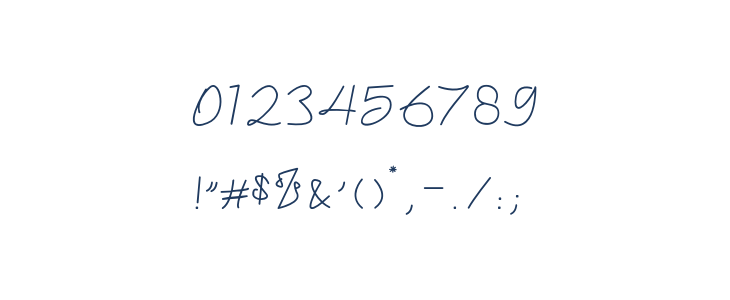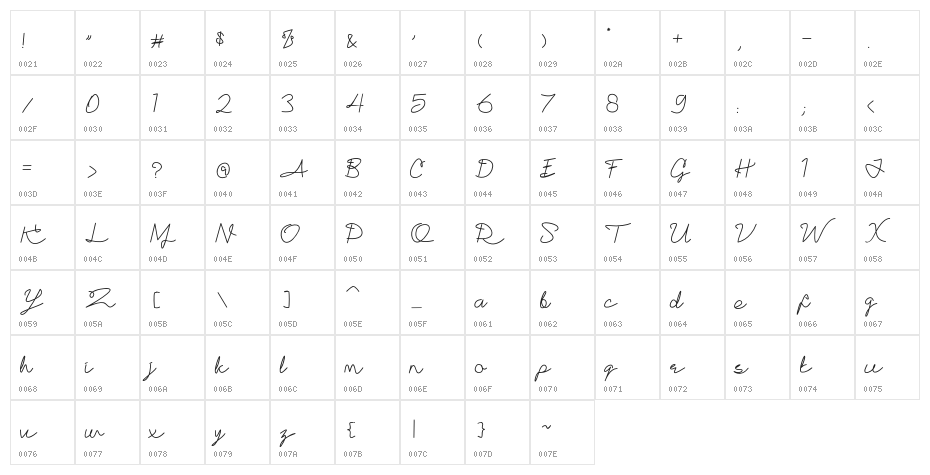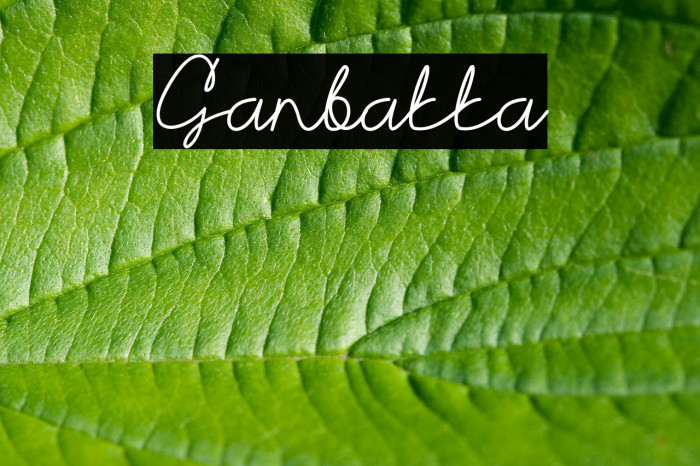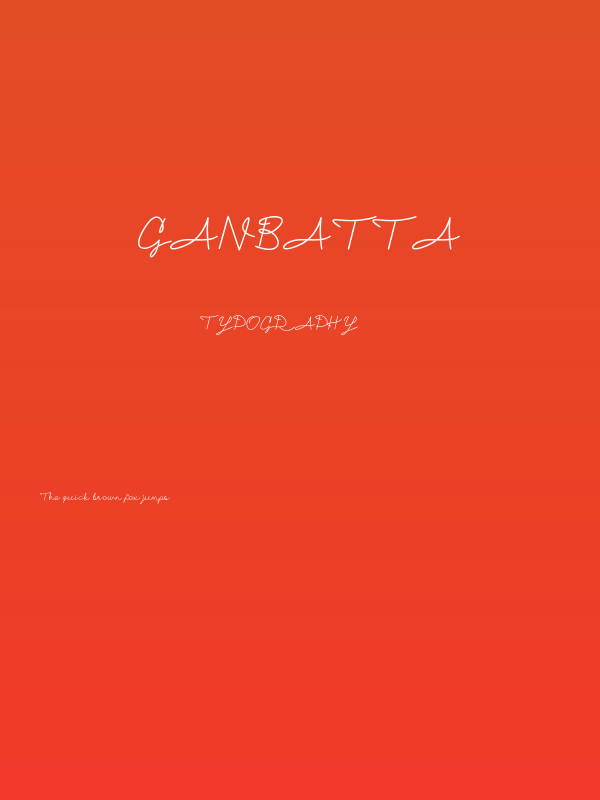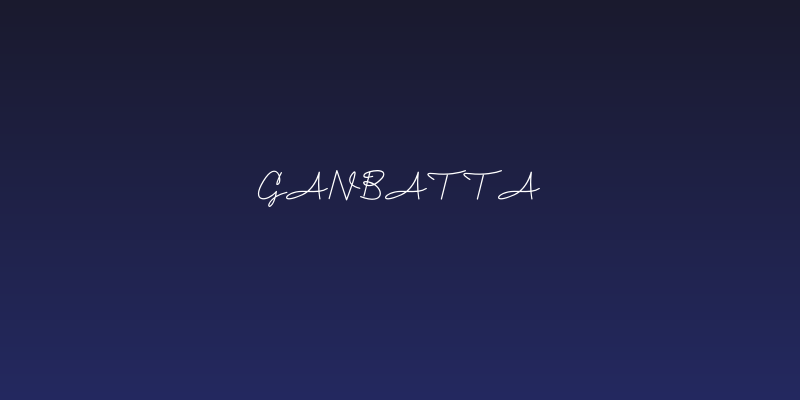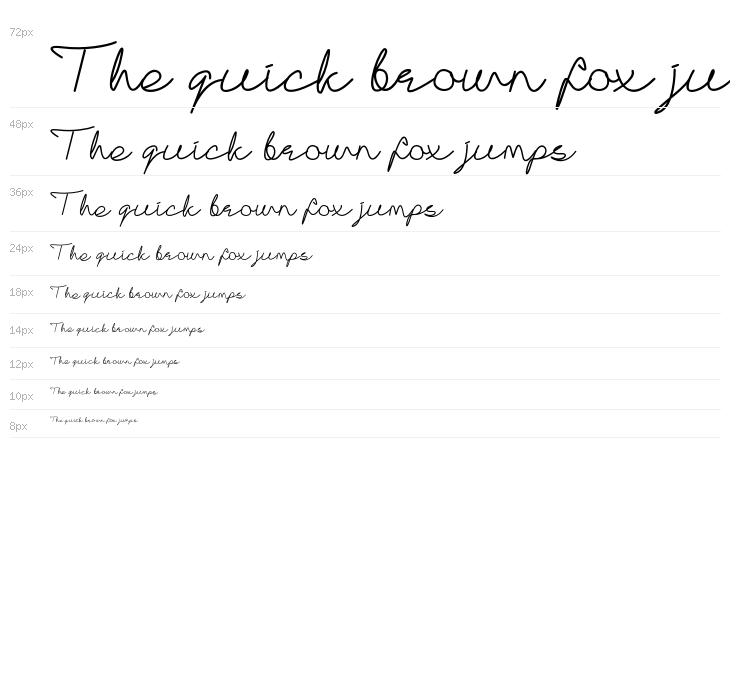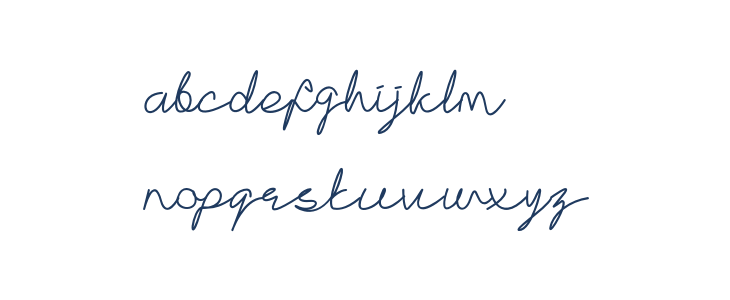
Ganbatta Font
| Gesamtstil | Elegant, Handwritten |
| Anwendungsfall | Logos, Invitations, Personal Branding |
| Vorgeschlagene Projekte | Ideal for wedding invitations, personal branding, greeting cards, and elegant stationery. |